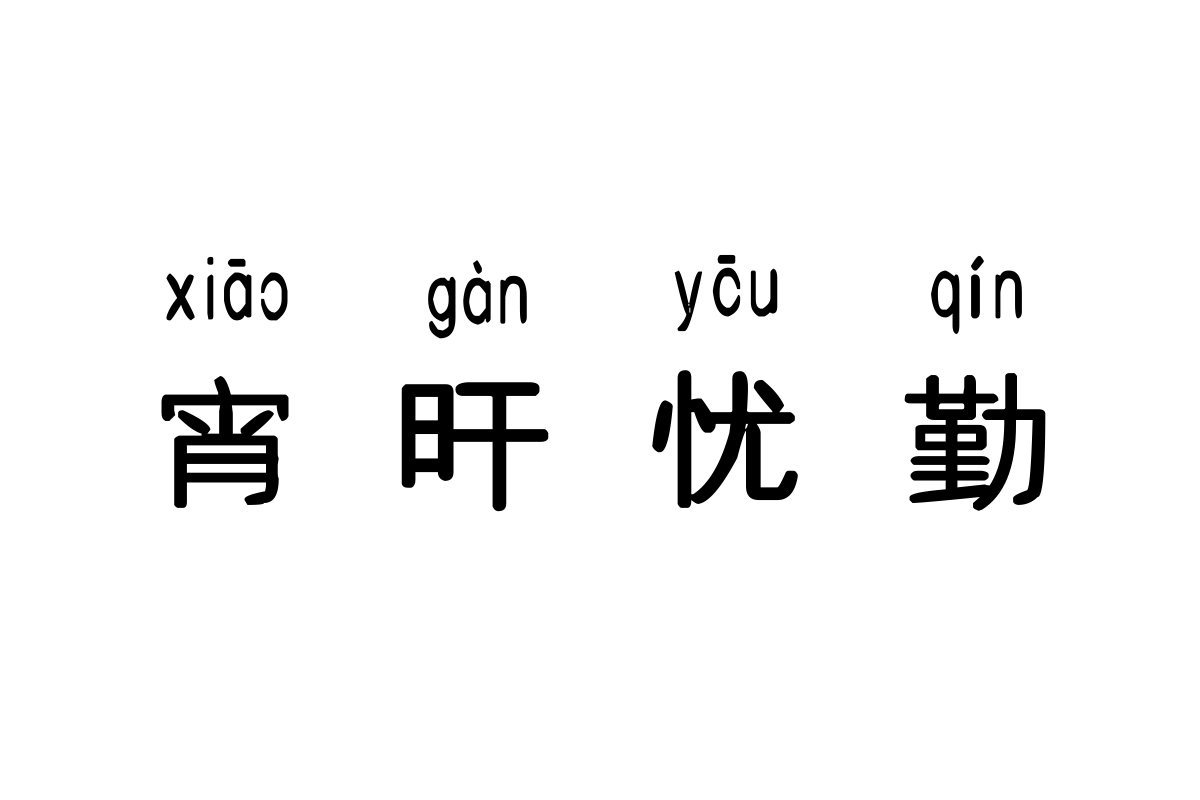
汉标粗圆拼音字体是一款具有独特风格的中文字体。它的特点是字形饱满,笔画粗壮,给人一种力量感和稳重感。这种字体非常适合用于标题、正文等需要强调文字重要性的场景。
汉标粗圆拼音字体的笔画粗细适中,既不会过于繁琐,也不会过于简单。它的每个字都经过精心设计,使得整个字体看起来既有美感又不失实用性。同时,由于其笔画粗壮的特点,也使得它在视觉上具有一定的冲击力,能够吸引人们的注意力。
总的来说,汉标粗圆拼音字体是一款非常实用的中文字体。无论是用于印刷还是电子显示,都能够展现出其独特的魅力。